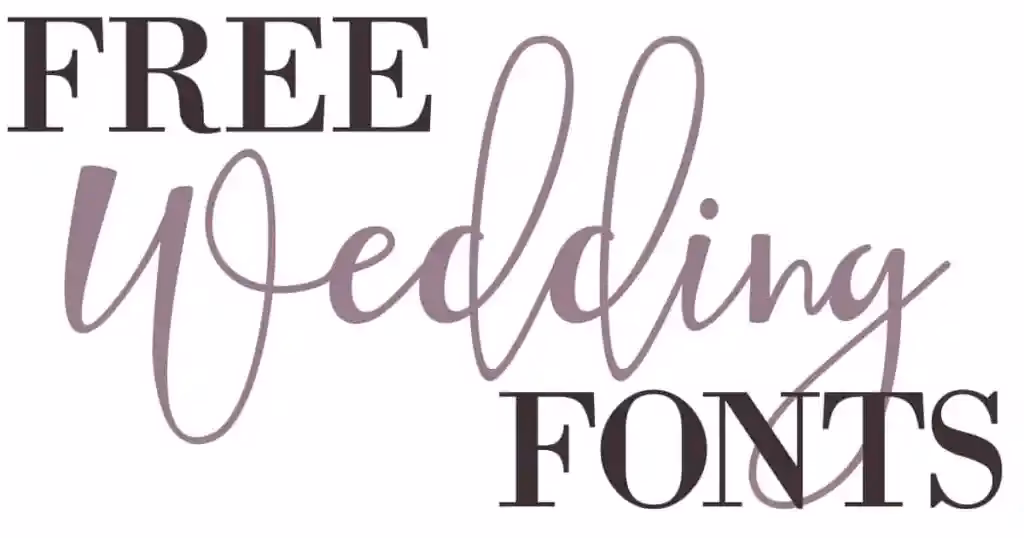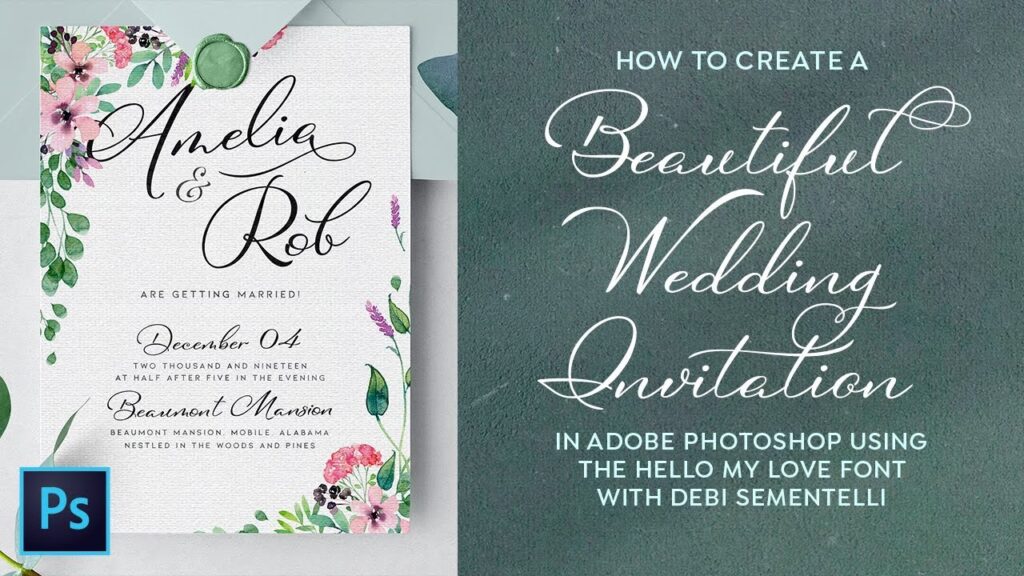
Valget af skrifttype til jeres bryllupsinvitationer og øvrige papirvarer er en afgørende detalje, der i høj grad bidrager til at forme jeres gæsters første indtryk af den store dag. Det handler om mere end bare tekst; det er en visuel repræsentation af jeres stil, jeres tema og den følelse, I ønsker at formidle. En velvalgt skrifttype kan udstråle elegance, modernitet, romantik eller legende lethed, og den rigtige kombination af skrifttyper kan løfte jeres design fra almindeligt til helt ekstraordinært. At finde den perfekte skrifttype-parring kan virke overvældende, men det er også en vidunderlig mulighed for at tilføje et personligt og sofistikeret præg.
Vælg din Hoved- eller 'Helte'-Skrifttype
Når I begynder designprocessen for jeres bryllupsinvitationer, er det første skridt at vælge en primær skrifttype, ofte omtalt som 'helte-skrifttypen'. Denne skrifttype vil være den mest fremtrædende på invitationen og sætte tonen for resten af teksten. Det er vigtigt, at denne skrifttype ikke kun er æstetisk tiltalende, men også let at læse. Husk, at invitationen skal formidle vigtig information tydeligt. Helte-skrifttypen bør afspejle det overordnede tema og den stil, I har valgt til jeres bryllup. Er I til et klassisk og formelt bryllup, vil en elegant serif-skrifttype måske være det rette valg. Foretrækker I et moderne og minimalistisk udtryk, kunne en stilren sans-serif skrifttype passe bedre. Til et romantisk eller vintage-inspireret bryllup kunne en smuk skriveskrift være ideel.
Kunsten at Parre Skrifttyper
Når I har valgt jeres helte-skrifttype, kommer den spændende del: at finde den eller de skrifttyper, der komplementerer den bedst muligt. At parre skrifttyper handler om at skabe balance og visuel harmoni. Målet er, at skrifttyperne arbejder sammen om at skabe et smukt og læsbart design, ikke at de konkurrerer om opmærksomheden.
Parring af Skrifttyper med Lignende Visuel Vægt
En effektiv metode til at skabe balance er at vælge en sekundær skrifttype med en visuel vægt, der enten ligner helte-skrifttypen eller skaber en bevidst, behagelig kontrast. Hvis jeres helte-skrifttype er en tyk og fed serif, kan en tyndere sans-serif skabe en fin balance. Omvendt kan en let skriveskrift parres med en mere robust serif eller sans-serif for at sikre, at den vigtigste information står klart frem. I kan også eksperimentere med kun at bruge én skrifttype, men variere størrelse, vægt (fed/normal) og stil (kursiv) for at skabe visuel interesse og hierarki i teksten. Dette kan give et meget rent og sammenhængende udtryk.
Kombinationen af Skriveskrift og Sans-Serif
Skriveskrift-skrifttyper er utroligt populære til bryllupsinvitationer på grund af deres romantiske og personlige udtryk. Dog kan de være svære at læse i større tekstblokke eller for personer med nedsat syn. Hvis I vælger en skriveskrift som jeres helte-skrifttype, er det ofte en god idé at parre den med en klar og enkel sans-serif skrifttype til brødteksten (f.eks. information om tid og sted). Kontrasten mellem den dekorative skriveskrift og den rene sans-serif gør teksten lettere at afkode, samtidig med at designet bevarer et elegant og sofistikeret udseende. Denne parring er en klassiker inden for bryllupsdesign af en god grund – den kombinerer det personlige med det praktiske.
Begræns Antallet af Skrifttyper
Selvom det kan være fristende at bruge mange forskellige skrifttyper for at skabe variation, er det vigtigt at begrænse antallet for at undgå, at designet virker rodet eller uharmonisk. Som en generel regel er to skrifttyper ofte tilstrækkeligt for de fleste designs. En til overskrifter/navne (helte-skrifttypen) og en til brødtekst. Hvis I ønsker mere variation, kan I, som nævnt, bruge forskellige vægte eller stilarter inden for de valgte skrifttyper. At holde sig til et begrænset antal skrifttyper hjælper med at skabe et professionelt og sammenhængende udtryk, der er behageligt for øjet.
Vigtige Overvejelser ved Valg af Skrifttype
Udover æstetikken er der flere praktiske faktorer, I bør overveje, når I vælger skrifttyper til jeres bryllupspapirvarer:
Passer Skrifttypen til Jeres Bryllupstema?
Skrifttypen skal forstærke og komplementere jeres overordnede tema. Et rustikt bryllup kalder måske på en håndskrevet eller lidt grovere skrifttype, mens et glamourøst bryllup passer bedre med en elegant og stilren skrifttype. Tænk over den stemning, I ønsker at skabe, og vælg skrifttyper, der understøtter denne stemning.
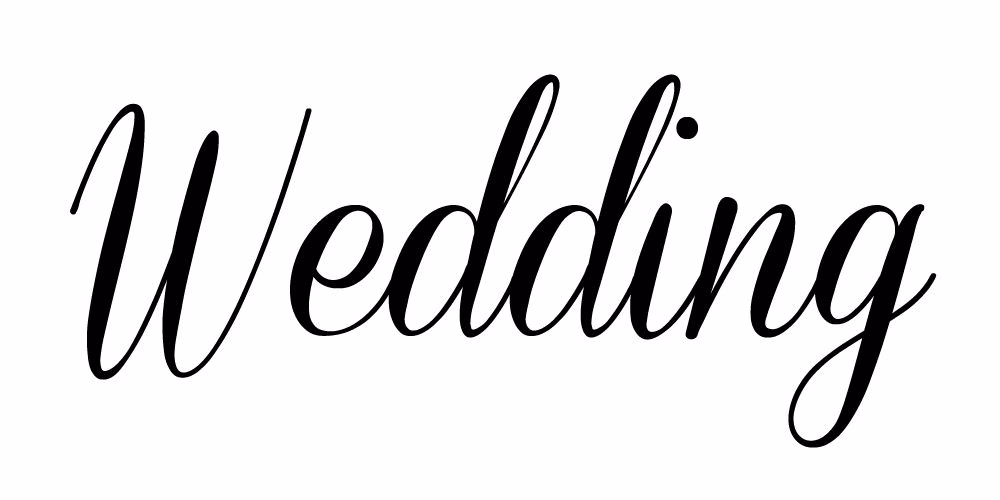
Er Skrifttypen Læsbar?
Dette er måske den vigtigste faktor. En smuk skrifttype er ubrugelig, hvis jeres gæster ikke kan læse den. Vær særligt opmærksom på skriveskrift-skrifttyper og meget tynde eller dekorative skrifttyper, især i mindre størrelser. Print altid en prøve ud for at teste læsbarheden i den faktiske størrelse, I planlægger at bruge.
Bør I Bruge Accent-Skrifttyper?
En accent-skrifttype kan bruges strategisk til at fremhæve specifikke informationer, såsom jeres navne eller bryllupsdatoen. Dette er ofte en tredje skrifttype, der adskiller sig markant fra de andre og bruges sparsomt for at skabe visuelt fokus. En fed skriveskrift kan være en fantastisk accent til et navn på en ellers minimalistisk invitation.
Populære Skrifttyper til Bryllupsinvitationer
Der findes tusindvis af skrifttyper, men nogle har etableret sig som favoritter inden for bryllupsdesign på grund af deres elegance, læsbarhed og alsidighed. Her er et udpluk af ofte efterspurgte skrifttyper:
At vælge skrifttyper til jeres bryllupspapirvarer er en kreativ proces, der giver jer mulighed for at sætte et personligt præg på jeres store dag allerede fra invitationen sendes ud. Tag jer tid til at udforske mulighederne, eksperimenter med forskellige kombinationer, og vælg de skrifttyper, der føles helt rigtige for jer og jeres kærlighedshistorie.